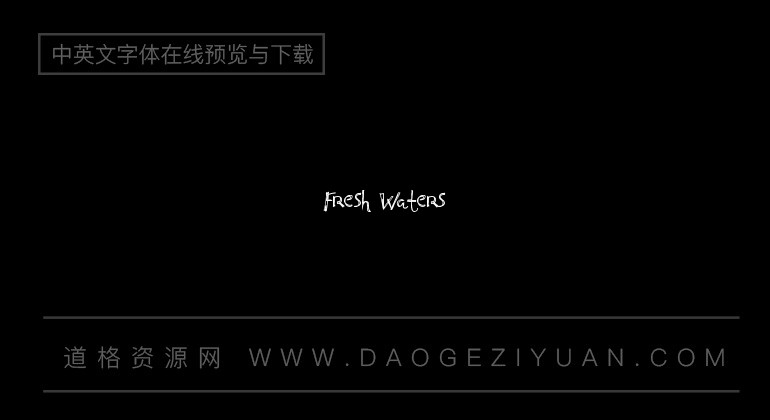
Fresh Waters是一种具有流畅线条和现代感觉的字体。它具有圆润的形状,同时保留了传统字体的一些特征,使它既时尚又易读。Fresh Waters由设计师 Yunita Ecy 创建,其字母间距离和字母形态都经过精心调整,以确保最佳的阅读和视觉效果。这种字体适用于各种设计项目,如标志、海报、杂志、网站等。它有几种不同的字体样式,包括粗体、斜体和正常样式,可以用来突出强调或提供多样性。内容介绍
Fresh Waters是一款非常不错的手写艺术字体,具有很好的视觉感,适合于文化类的宣传设计、商业类品牌的广告和产品包装设计以及个性化文字排版等较多场景。